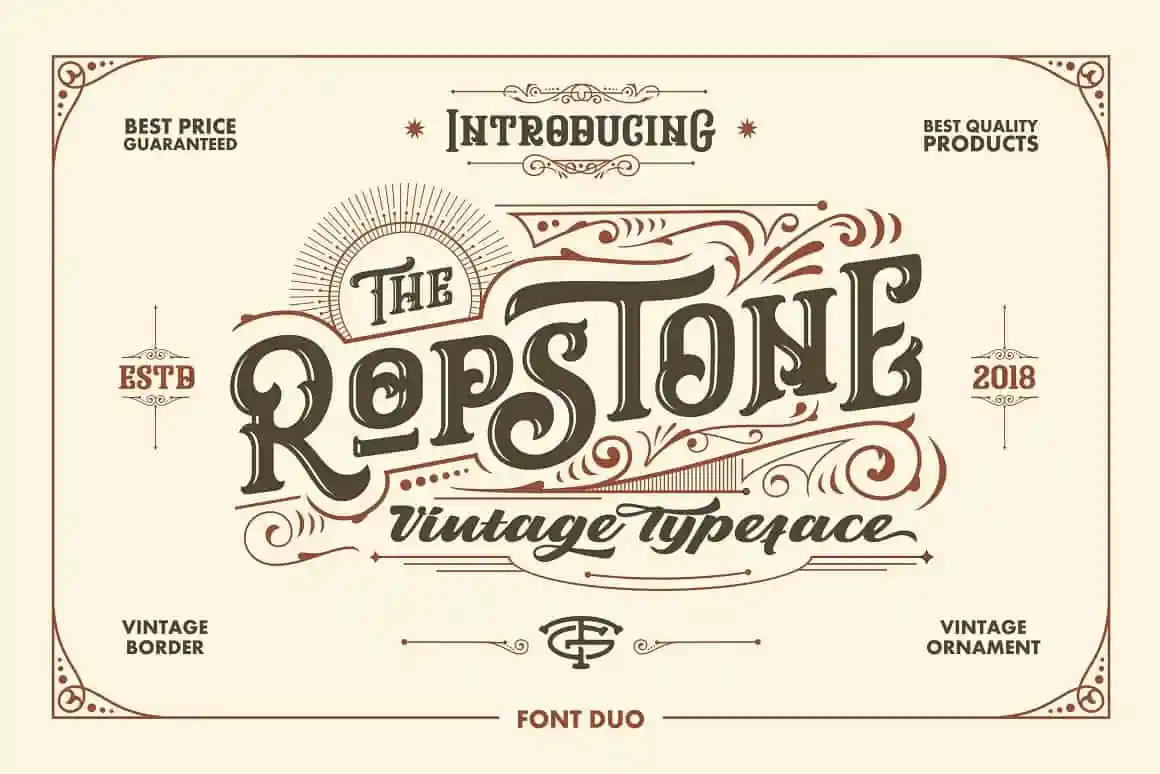
A Ropstone Typeface é uma nova tipografia vintage apresentada pela Graptail. Ela foi criada a mão inspirada nos clássicos posters e traz um toque de nostalgia para qualquer obra que você criar com ela. A Ropstone, uma fonte display desenvolvida de forma cuidadosa e meticulosa, é ideal para aqueles que buscam um retorno ao passado nas criações digitais. Inspirada em elementos dos anos 40 a 60, essa font oferece uma experiência visual vívida e inspiradora. Seja você designer de gráficos ou simplesmente alguém que aprecia esse estilo vintage, a Ropstone atende perfeitamente para trazer um toque nostálgico às suas criações digitais. Não esperamos mais. Os preços estão acessíveis e o melhor do seu investimento está garantido com esta fonte de alta qualidade, criada pela Hamilton.